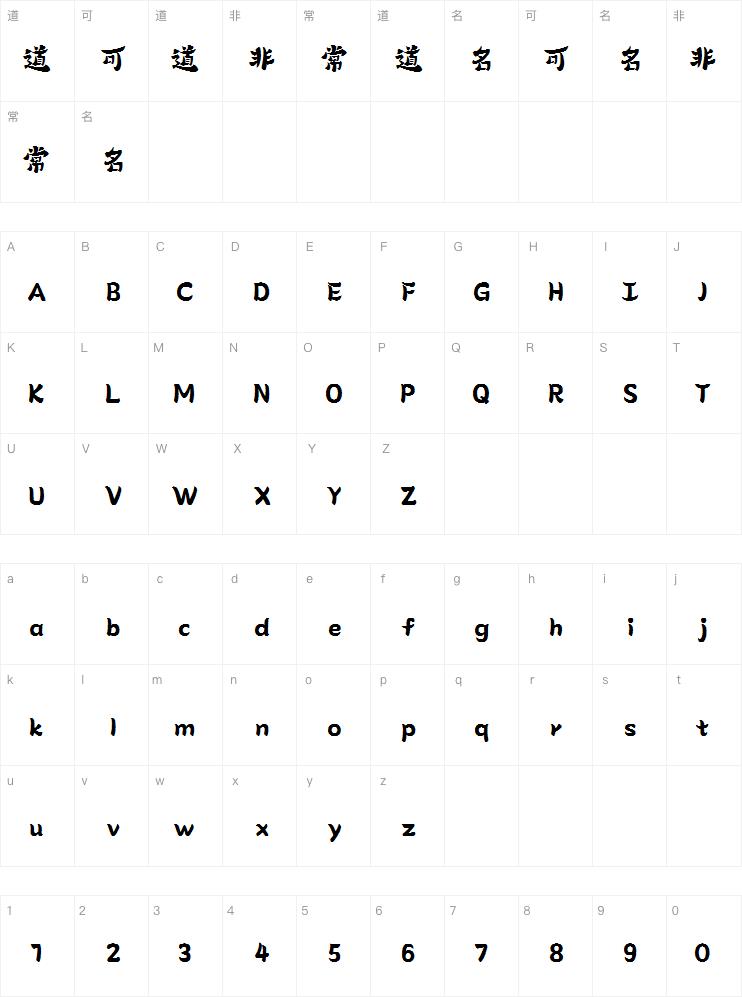
山海竹叶青w
山海竹叶青,是一款全新的字体,包含汉字9169个,符号200+个。该字体是一款卡通风字体,该字体字形灵动多变,童趣可爱,同时融入手写风笔势,笔画造型形似竹叶,整体笔触圆润,活泼清新,造型生动有趣,具有灵活的适用性,天真俏皮又不失时尚感。该字体字形随手写习惯大小不一,各个字的大小随字形的不同而呈现不同的大小,但是在变化中寻求平衡,在多变的同时有保持整体均衡匀称,使得整个字体更具有手写感的温度和节奏感,整体笔触圆润,灵动笔画贯穿笔画始终,内涵丰富,弧度柔和,撇笔平缓舒展,尽显俏皮灵动。